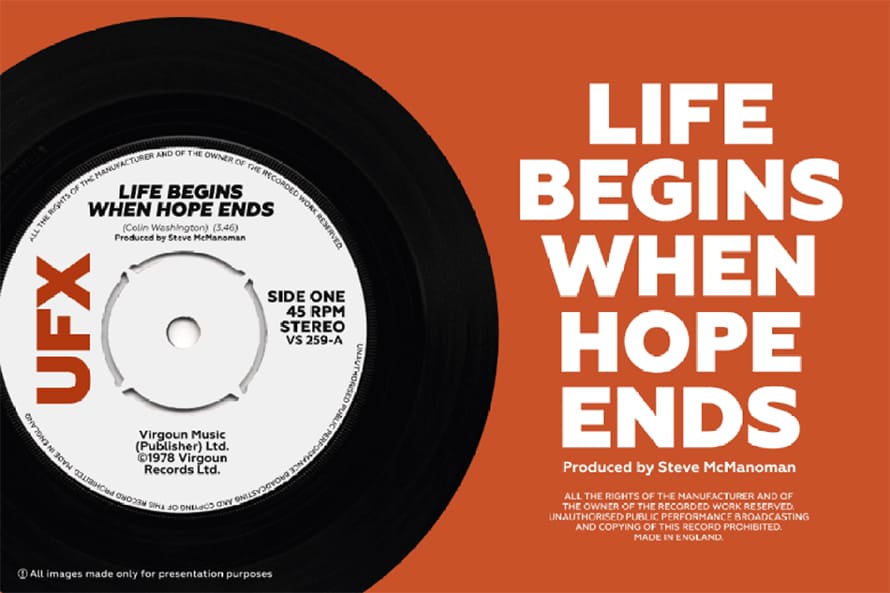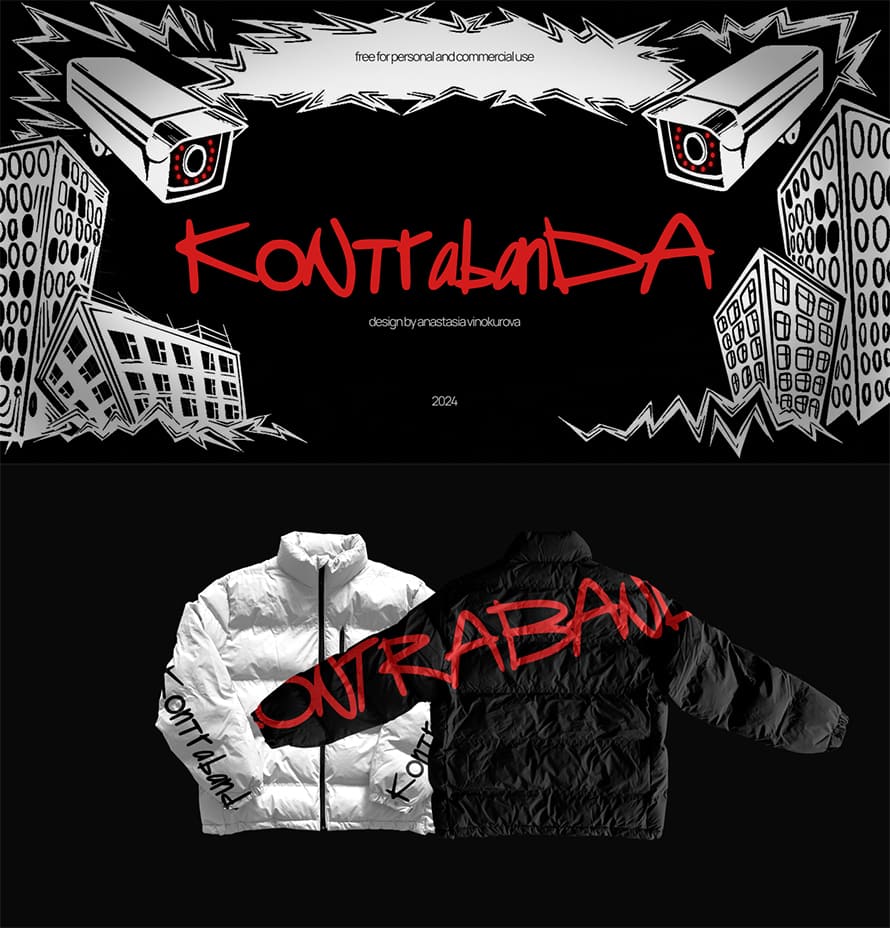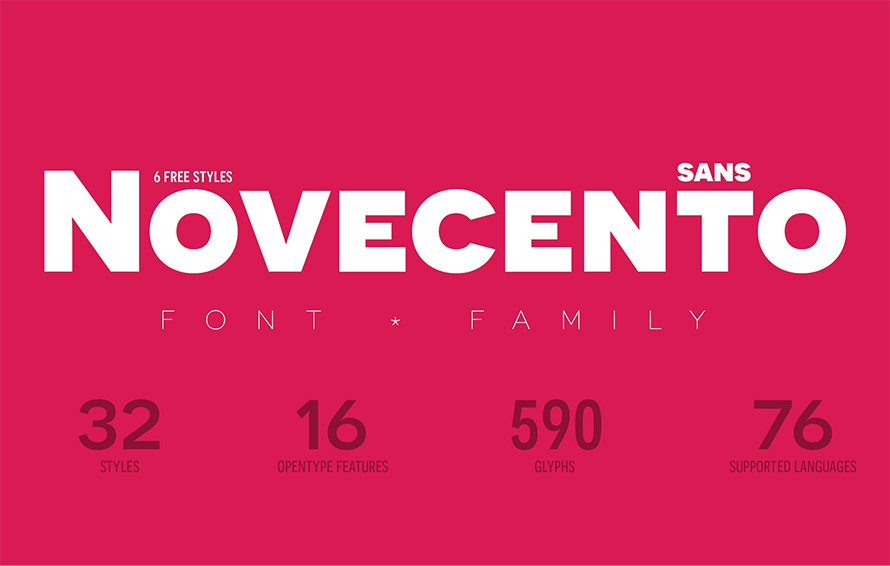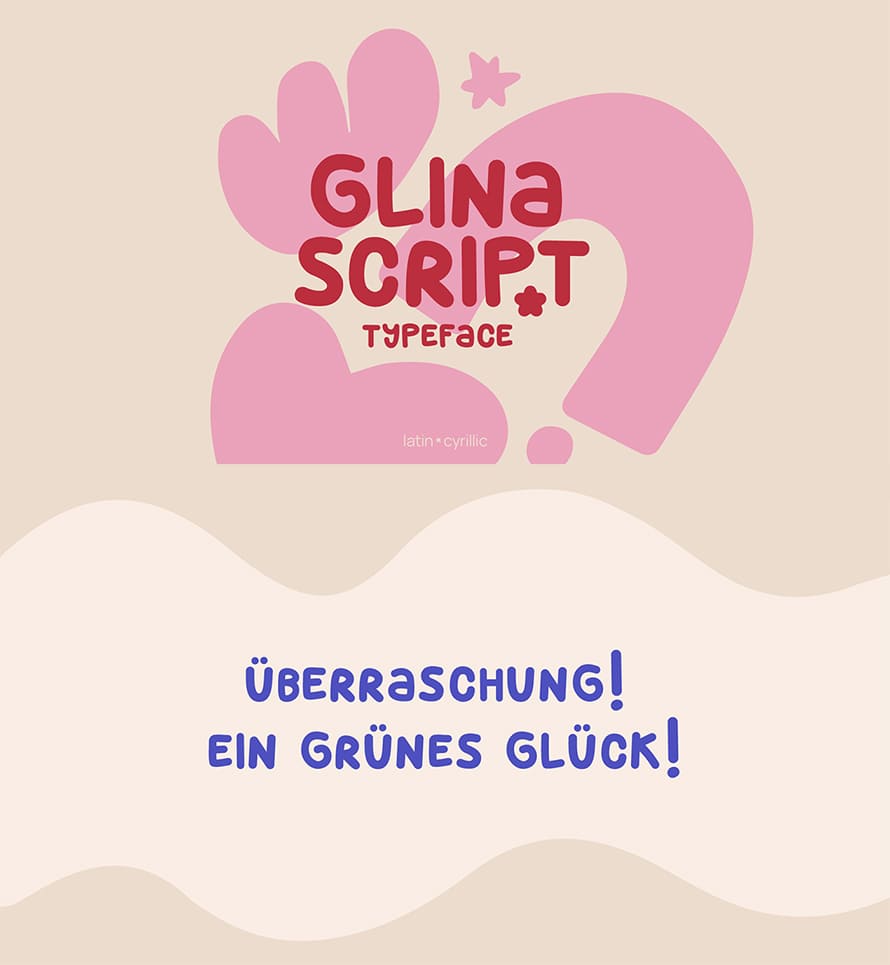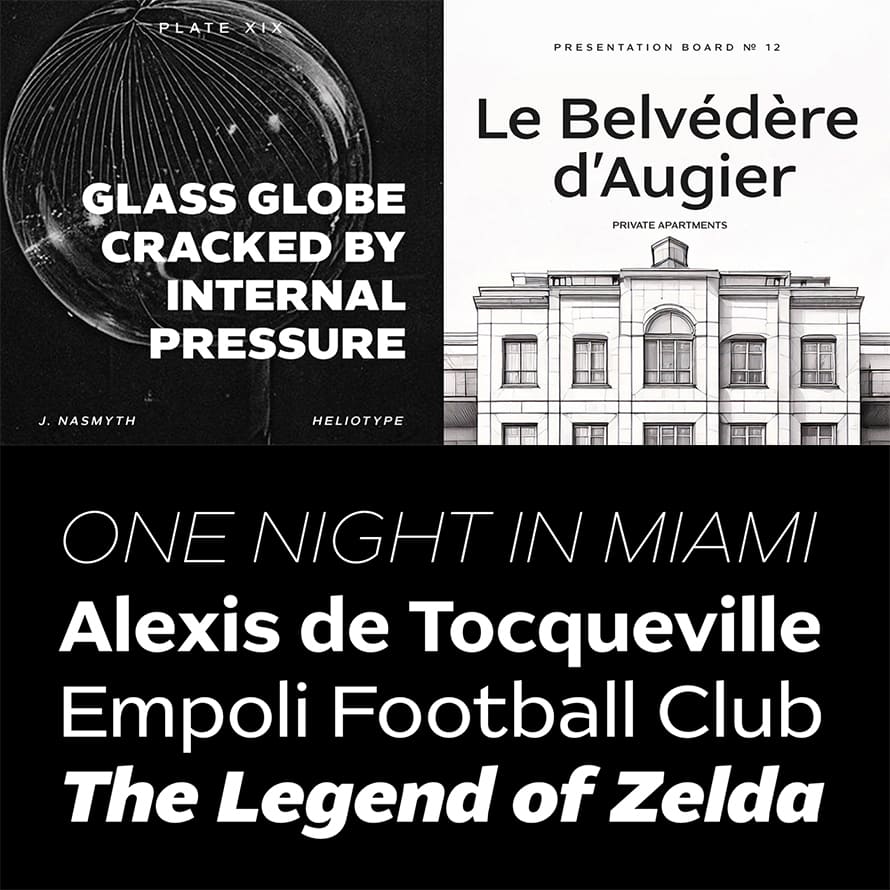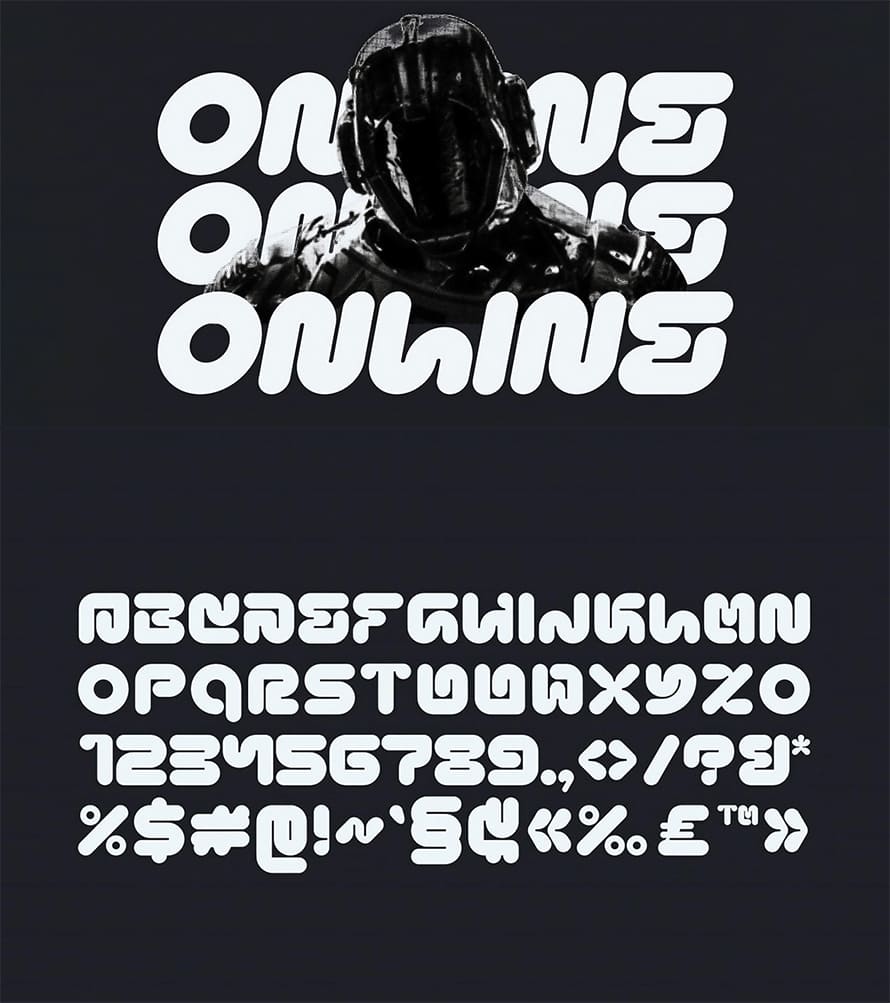
Typografie bestimmt, wie Menschen Texte lesen und empfinden. Hochwertige Schriftarten verbessern die Klarheit und unterstützen die visuelle Identität. Viele Designer suchen nach hochwertigen Schriftarten, die kostenlos sind. Dieser Artikel stellt neue kostenlose Schriftarten vor, die du herunterladen und uneingeschränkt nutzen kannst. Jede dieser Schriftarten eignet sich sowohl für private als auch kommerzielle Projekte.
Diese Typografien stammen von unabhängigen Designern und Open-Source-Bibliotheken. Sie umfassen eine breite Palette an Stilen – einige folgen einem minimalistischen Design, andere vermitteln Präsenz durch kraftvolle Ausdrucksstärke. Jede aufgeführte Schriftart erlaubt dir, sie ohne Kosten zu verwenden. Keine versteckten Gebühren. Keine Namensnennung erforderlich. Einfach herunterladen und loslegen.
Manche Schriftarten sind optimiert für Lesbarkeit auf Bildschirmen, andere sind besser geeignet für Druckmaterialien. Alle bieten klare Konturen und funktionieren plattformübergreifend. Designer setzen diese Schriftarten in Markenidentitäten, Weblayouts, Plakate und Verpackungen ein. Sie passen sich sowohl kleinen als auch großflächigen Projekten an. Sie beinhalten überarbeitete Versionen klassischer Formen, orientieren sich teilweise an globalen Designtraditionen oder bauen auf modernen Trends auf. Du kannst sie mit anderen Schriftarten kombinieren und beliebig skalieren – sie behalten ihre Form bei unterschiedlichen Größen.
31 neue kostenlose Schriftarten zum Herunterladen für Grafikdesigner
Diese 31 Schriftarten kannst du kostenlos herunterladen und sie eignen sich sowohl für private als auch kommerzielle Projekte. Sie lassen sich in Branding-Konzepten, Webseiten, als Plakatschriftarten, Verpackungen, Social Media und Marketing einsetzen. Sie tragen zu klaren Designs bei und helfen dir, konsistente Gestaltung zu gewährleisten.
Mehrere Schriftarten aus dieser Sammlung haben kraftvolle Großbuchstaben, andere bieten ausgewogene Kleinbuchstabenformen, ideal für längeren Text. Du wirst sowohl Serifen- als auch Sans-Serif-Schriftarten finden. Einige Schriftarten zeigen geometrische Strukturen, andere wirken handgefertigt. Manche eigenen sich besser als Displayfonts, andere sind ideale Wahl für Fließtexte.
Kiloy Rounded Techno Font
Kiloy vermittelt den Eindruck ständiger Bewegung durch abgerundete, fließende Linien, die weichen Blasen ähneln und ein Gefühl sanfter Dynamik erzeugen. Sein spielerischer und einfacher Charakter wird harmonisch kombiniert, was eine sanfte visuelle Präsenz schafft. Die organische Fluidität des Fonts ruft Assoziationen mit futuristischem Design hervor und fügt einen modernen, dynamischen Akzent hinzu.
Kontrabanda New Font Free Font
Kontrabanda New Font ist eine stilvolle, moderne Schriftart, die als kostenlose Variante zur Verfügung steht. Sie zeichnet sich durch kraftvolle, kantige Buchstabenformen aus, die perfekt für Überschriften, Plakate und Branding geeignet sind. Ihr einzigartiges Design erzeugt einen starken visuellen Effekt und lässt jedes Projekt hervorstechen.
Glina Script Kostenlose Schriftarten
Glina ist eine handschriftliche Schriftart mit sanftem, elastischem Charakter. Entworfen für lateinische und kyrillische Zeichen in zwei Stilen, eignet sie sich besonders gut für Comics. Die Schriftart enthält außerdem Zahlen und einige Symbole.
Geoform Kostenlose Schriftart
Geometrische Schriftarten sind durch ihre Nutzung geometrischer Formen wie Kreise, Quadrate und Dreiecke gekennzeichnet. Diese Schriftarten betonen Klarheit und Struktur und erzeugen oft ein modernes und sauberes Erscheinungsbild, das Lesbarkeit und visuelle Ästhetik verbessert. Geometrische Schriftarten basieren auf einfachen Grundformen.
Artford Kostenlose Schriftarten
Artford ist eine benutzerfreundliche Sans-Serif-Schriftart, die für Vielseitigkeit gestaltet wurde. Ihre etwas breiteren Buchstaben und hohe x-Höhe machen sie ideal für auffällige Überschriften sowie kleine Textgrößen.
Novecento Sans Schriftart
Novecento Sans ist eine klare, geometrische Sans-Serif-Schriftart, inspiriert von der Typografie des frühen 20. Jahrhunderts. Mit ihren glatten, modernen Linien und vielseitigen Stilen ist sie ideal für Überschriften, Logos und Branding. Die Schriftart bietet mehrere Gewichte für flexible und professionelle Designanwendungen.